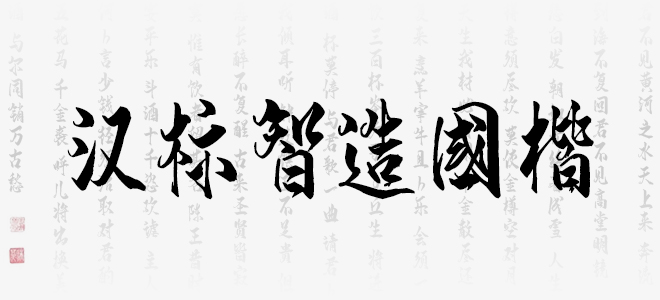
漢標智造國楷字體是漢標字庫推出的一款非常不錯的藝術(shù)字體,書法氣息濃厚,結(jié)字瀟灑俊逸,運筆行云流水,氣韻生動。適用于文藝類的書刊、品牌廣告和產(chǎn)品包裝設(shè)計,以及社交網(wǎng)絡(luò)的個性化用字,歡迎喜歡漢標智造國楷字體的朋友前來下載使用。
漢標智造國楷字體